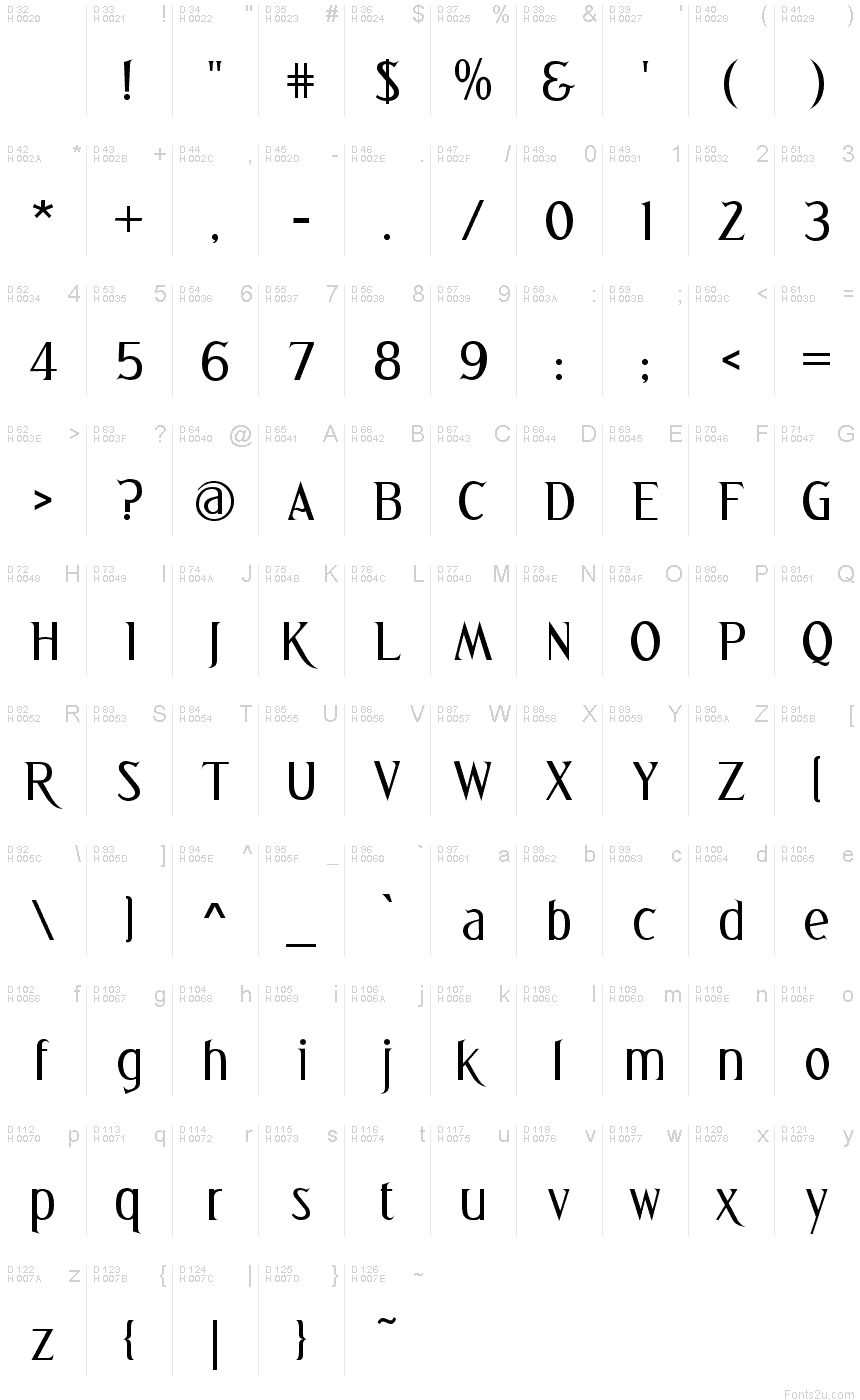
Greetings to darmowy krój szeryfowy autorstwa Richarda Williama Muellera, który sprawia wrażenie odręcznej notatki przeniesionej w metal. Litery są smukłe i lekko formalne, z wyraźnymi, zwężającymi się pociągnięciami i schludnymi szeryfami, które nadają każdemu słowu wyważony, niemal ceremonialny wyraz. Delikatny ruch w krzywiznach sprawia, że font nie wydaje się sztywny, dzięki czemu nagłówki i imiona wyglądają jednocześnie dostojnie i osobiście.
Wykorzystanie Greetings w projektach dodaje pełnego wdzięku, tradycyjnego charakteru zaproszeniom ślubnym, kartkom okolicznościowym, programom wydarzeń, okładkom książek, certyfikatom i klasycznym znakom logotypowym. Ten darmowy font najlepiej prezentuje się w większym rozmiarze, gdzie jego subtelne krzywizny mogą w pełni wybrzmieć; zestaw go z czystym bezszeryfowym krojem w tekście głównym, aby zachować przejrzystość i nowoczesny styl.
Dwa spiczaste fonty semi-serif w starym stylu, luźno inspirowane liternictwem z okładki 'My Book About Christmas' autorstwa Joan Gale Thomas z 1946 roku. Wersje Regular i Bold z 2017 roku oferują znaczące ulepszenia w zakresie obrysów i światła między znakami.